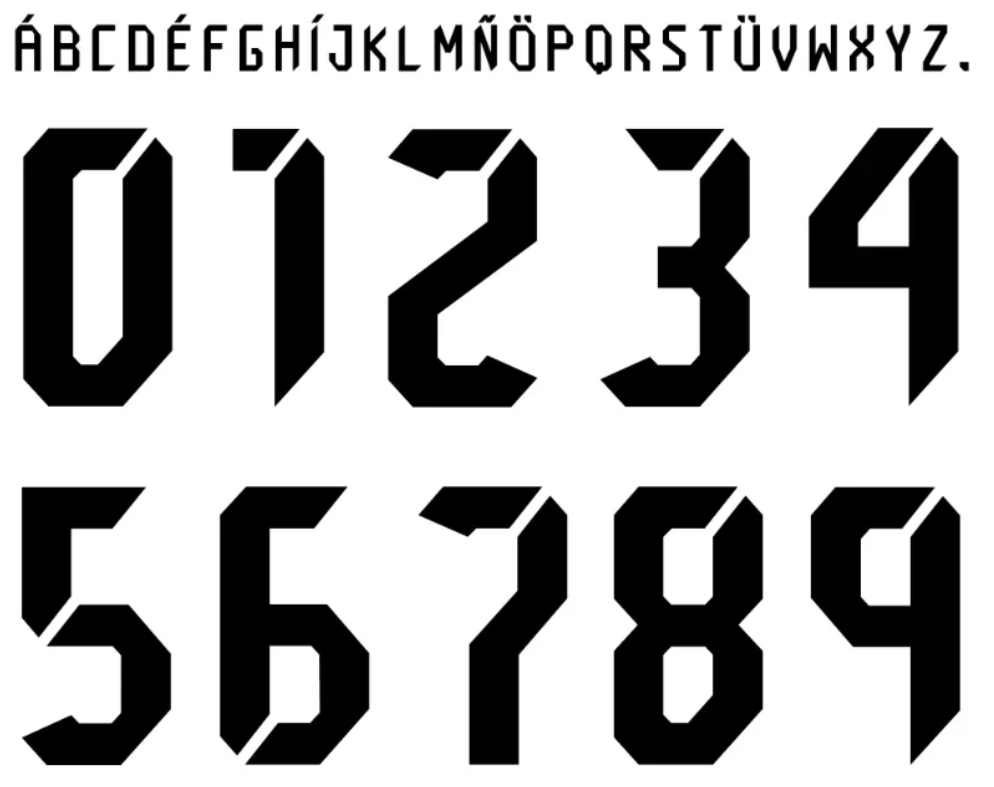
Salve, Fiel e apaixonados por design esportivo! Hoje trazemos um arquivo histórico e essencial para a sua coleção de personalização. Estamos falando da tipografia que estiou nas costas dos jogadores durante a campanha inesquecível do Heptacampeonato Brasileiro.
Em 2017, sob o comando de Fábio Carille e com gols decisivos de Jô, o Corinthians dominou o Brasil. A camisa daquela temporada, produzida pela Nike, carregava uma identidade visual que misturava a tradição de São Jorge com a modernidade agressiva que o “Time do Povo” exigia naquele ano. Agora, você pode baixar essa fonte exata para criar seus próprios projetos.
- Conjunto de Caracteres: Inclui numeração completa (0-9) e alfabeto maiúsculo padrão utilizado nas camisas de jogo.
🎨 Estilo Visual e Identidade
A fonte do Corinthians de 2017 segue o template global que a Nike utilizou naquela temporada, mas com personalizações exclusivas para o Timão.
Visualmente, ela transmite robustez. É uma fonte “sans-serif” (sem serifa) com ângulos retos e cortes estratégicos nas pontas dos números, o que confere uma sensação de velocidade e agressividade.
Um detalhe crucial para quem busca realismo: esta versão em TTF busca replicar o espaçamento e a espessura exata usada no manto alvinegro, ideal para quem quer restaurar uma camisa original ou criar uma réplica fiel do uniforme do Hepta.